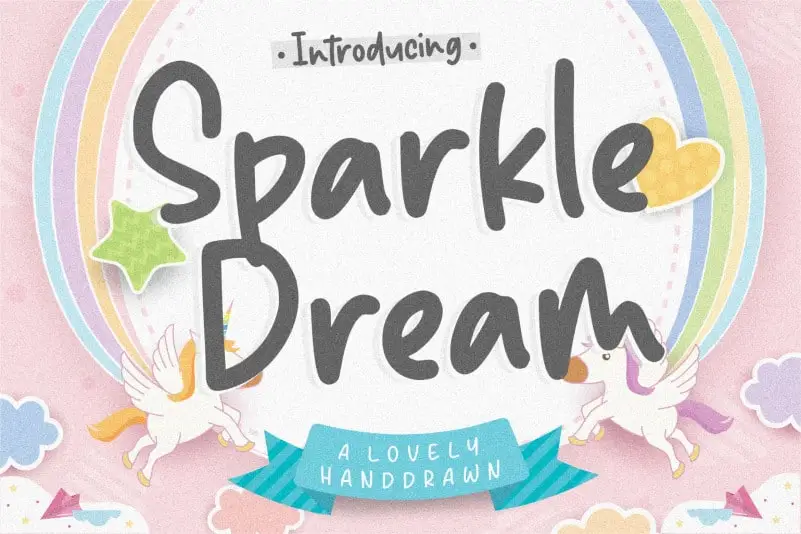
Sparkle Dream Lovely Handdrawn Font – Download Grátis
A fonte Sparkle Dream Lovely é uma escolha perfeita para qualquer projeto visual que exija uma sensação elegante e sofisticada. Desenvolvida pelo designer balpirick, essa font é especialmente adaptada para aplicativos como embalagens de produtos, projetos de marca, revistas, redes sociais, ou até mesmo destacar frases sobre um fundo, seja no contexto de um casamento ou em qualquer outra ocasião. Suas letras delicadas e oníricas transmitem uma energia brilhante e encantadora, tornando-a ideal para criar designs que chamem atenção e se assemelham a momentos mágicos. Ainda não experimentou a magia da Sparkle Dream Lovely? Então é hora de mergulhar nessa fonte cheia de vida, certamente irá revolucionar seu trabalho de design!